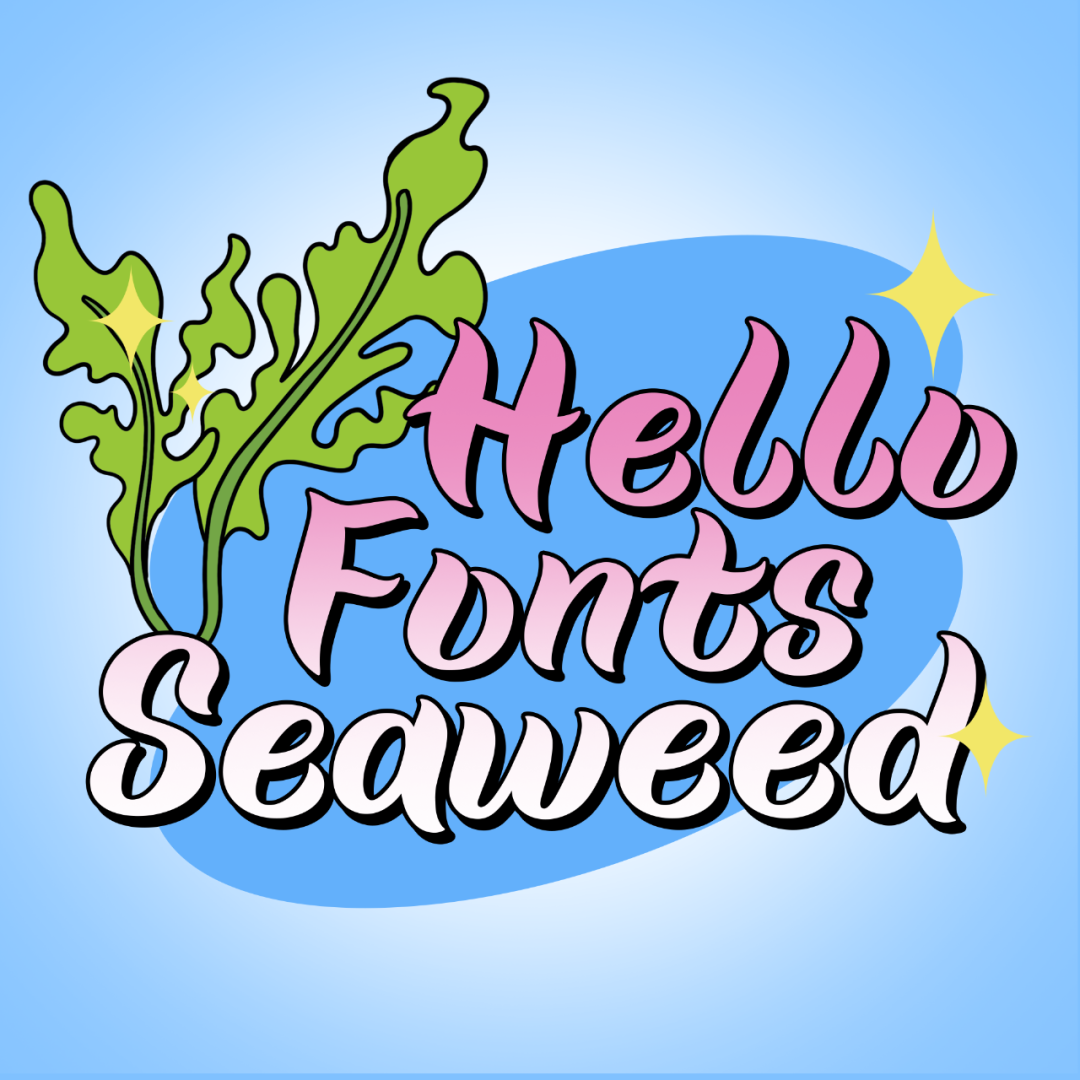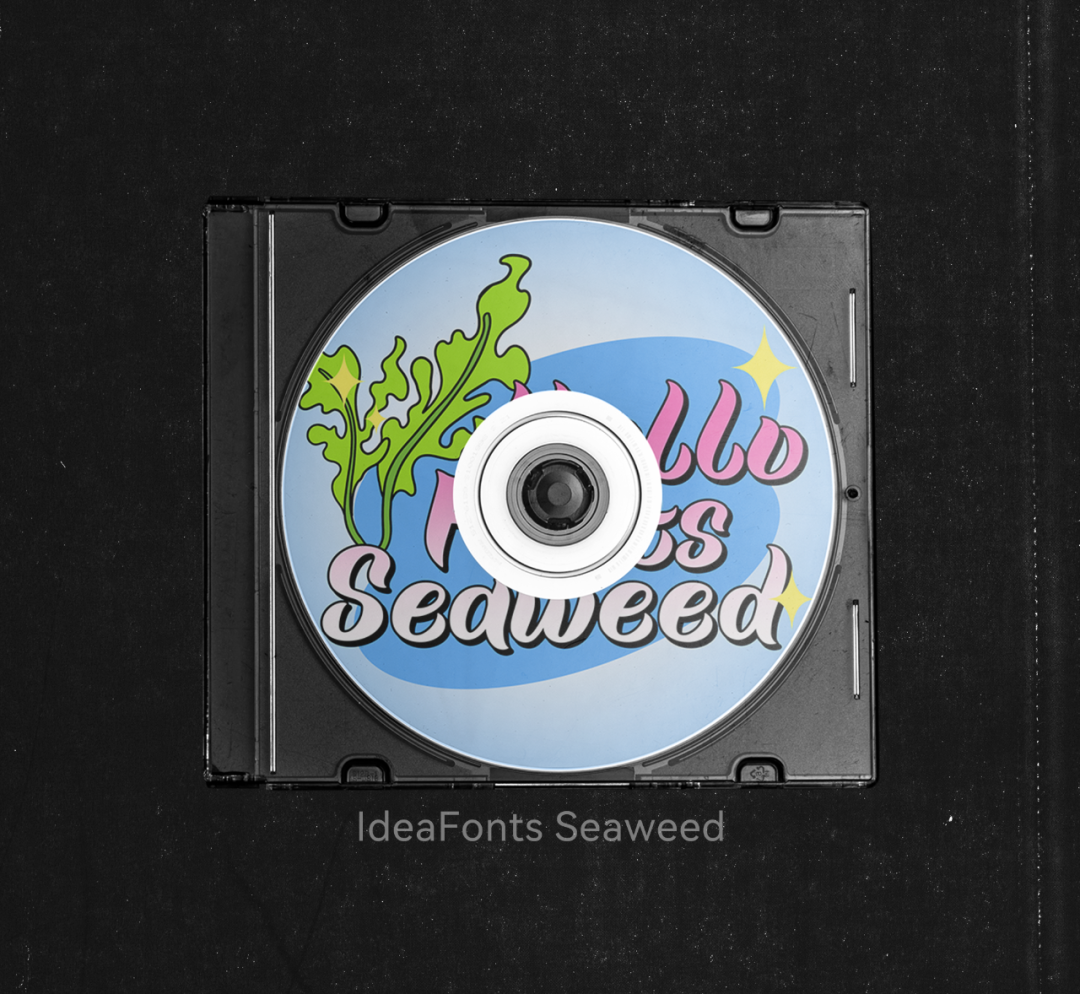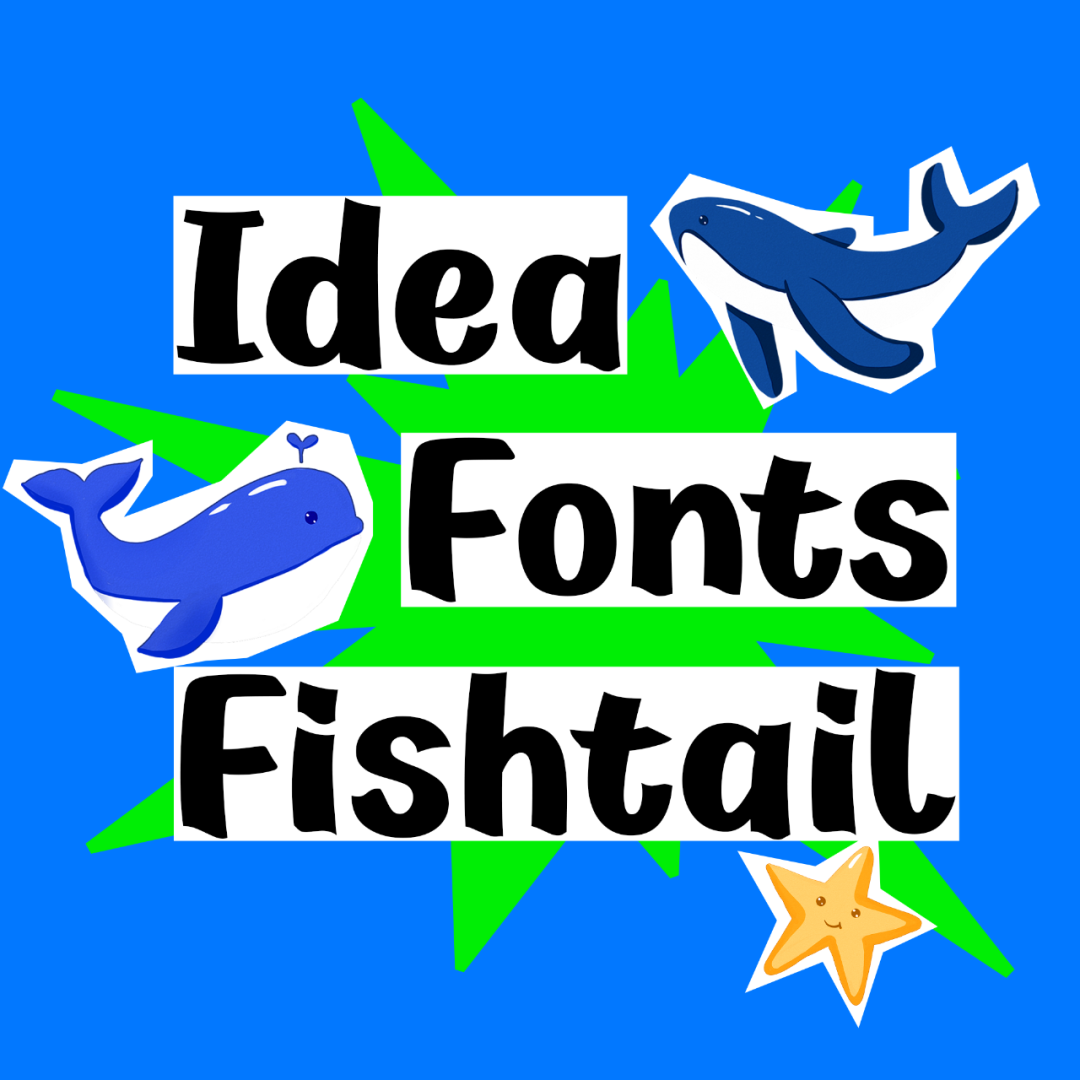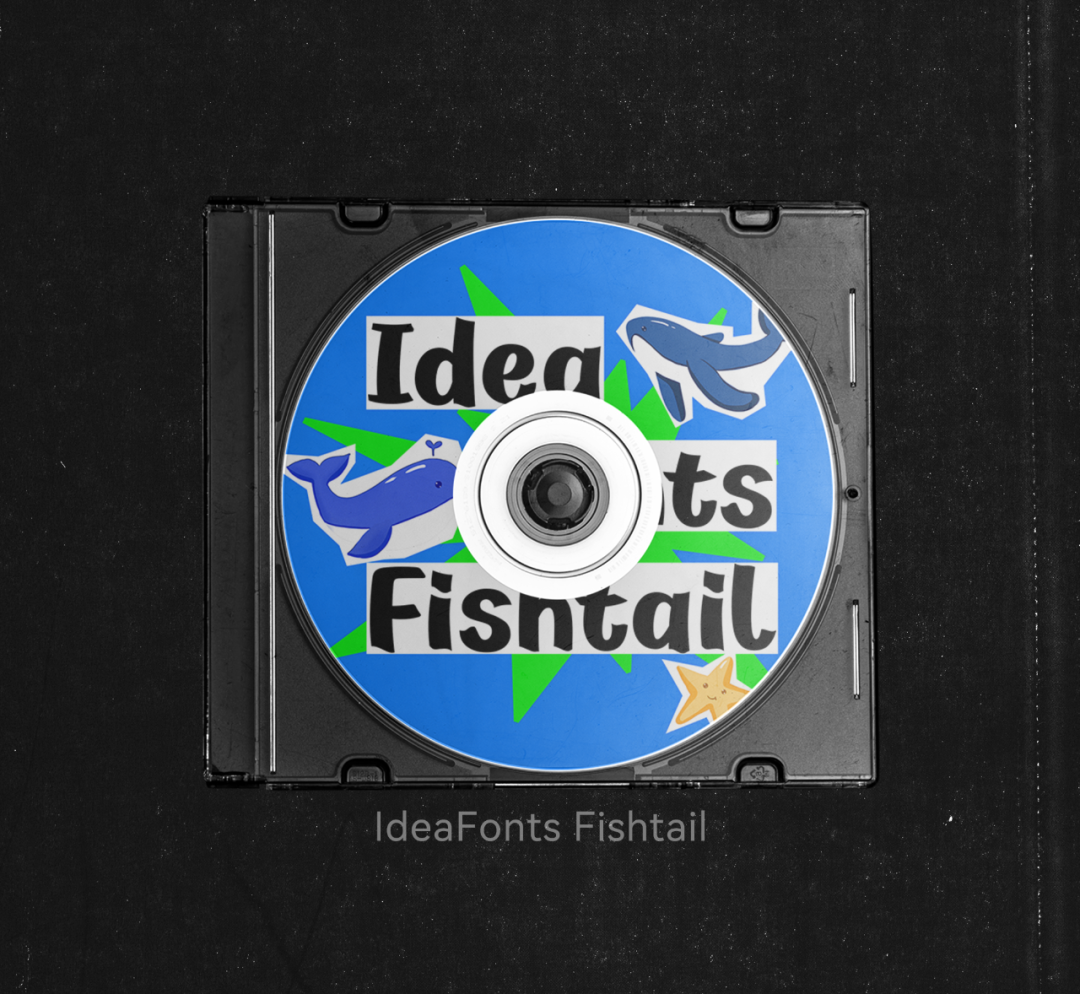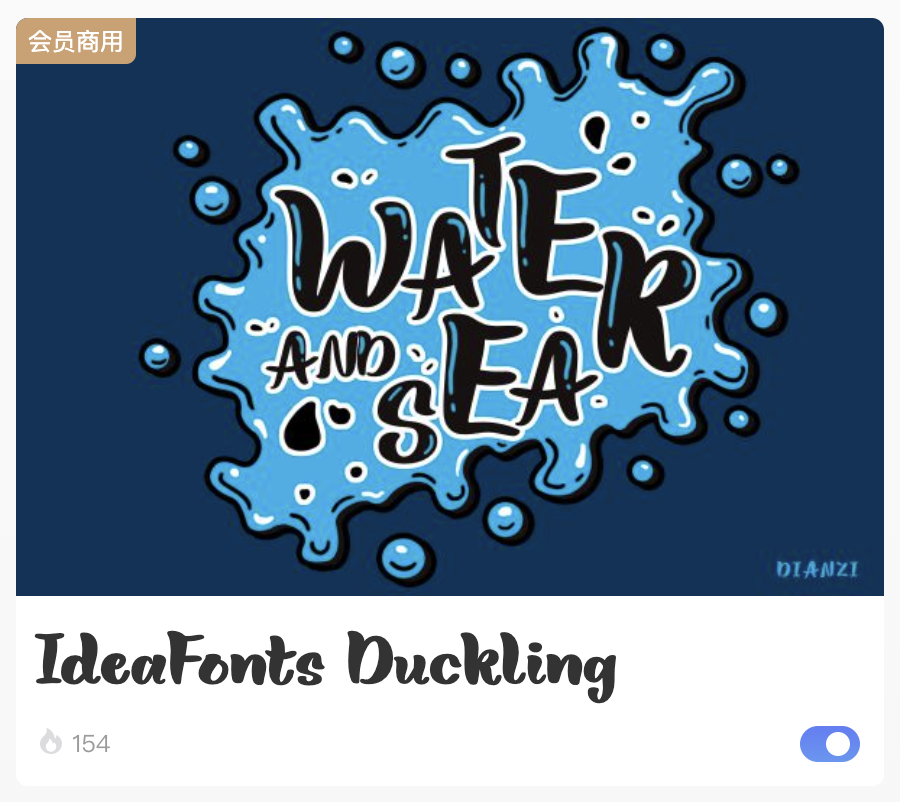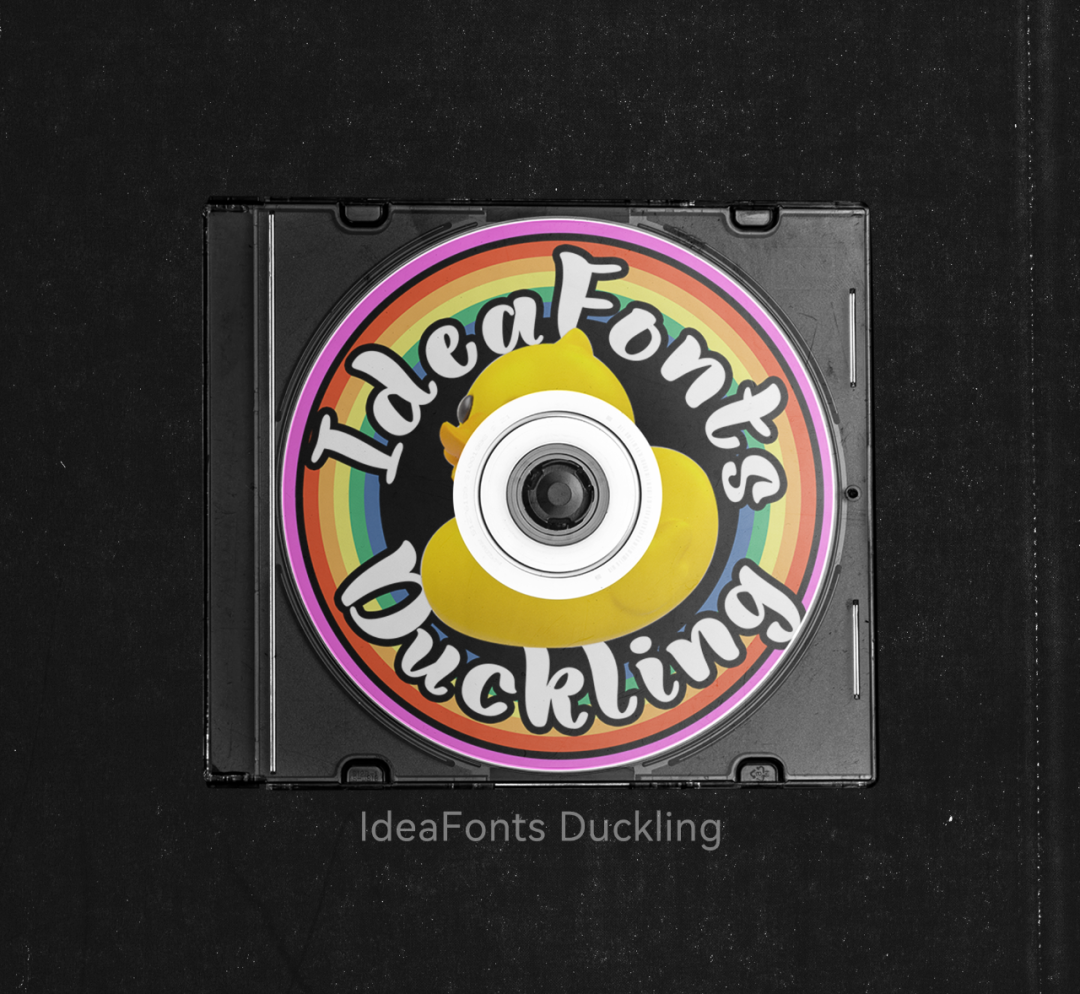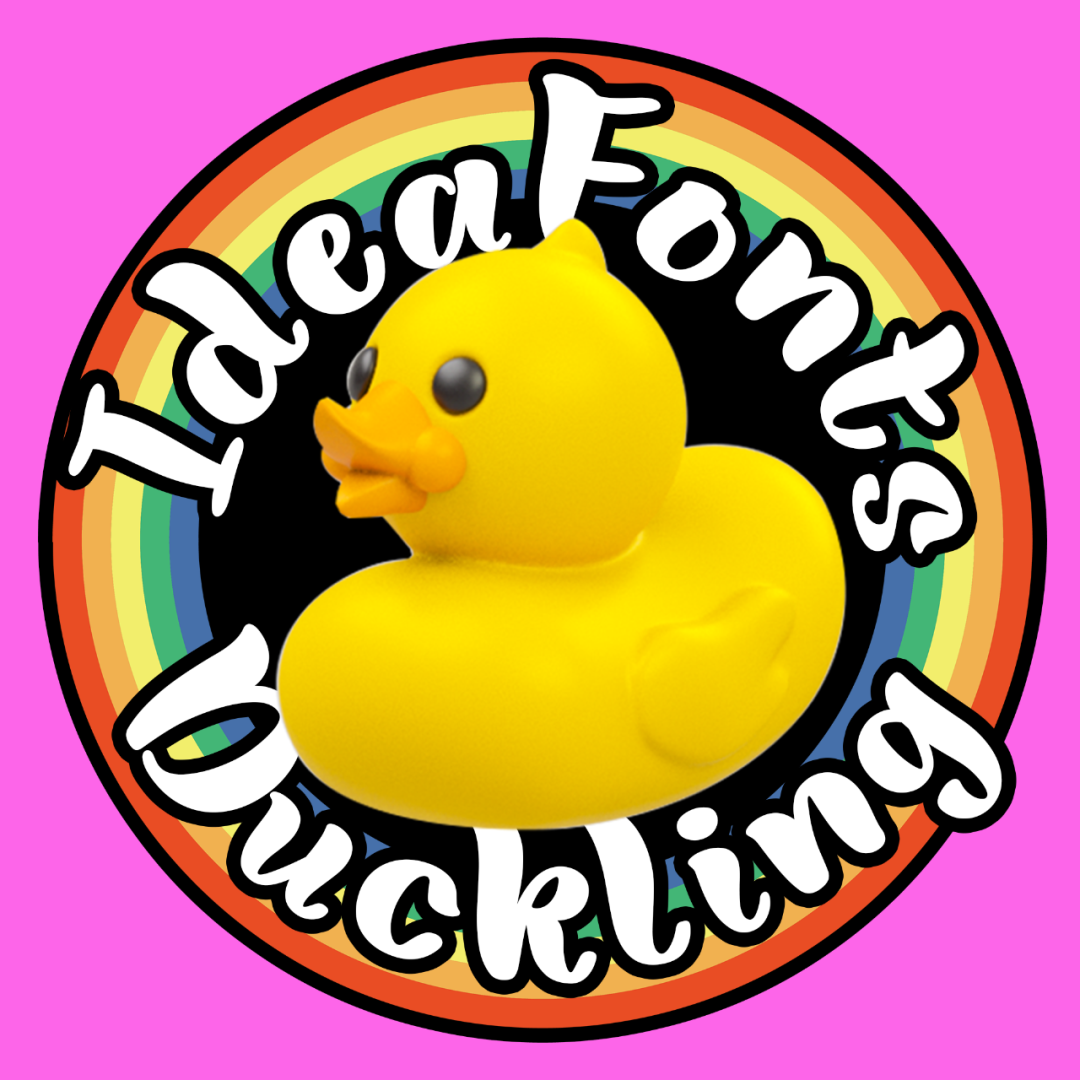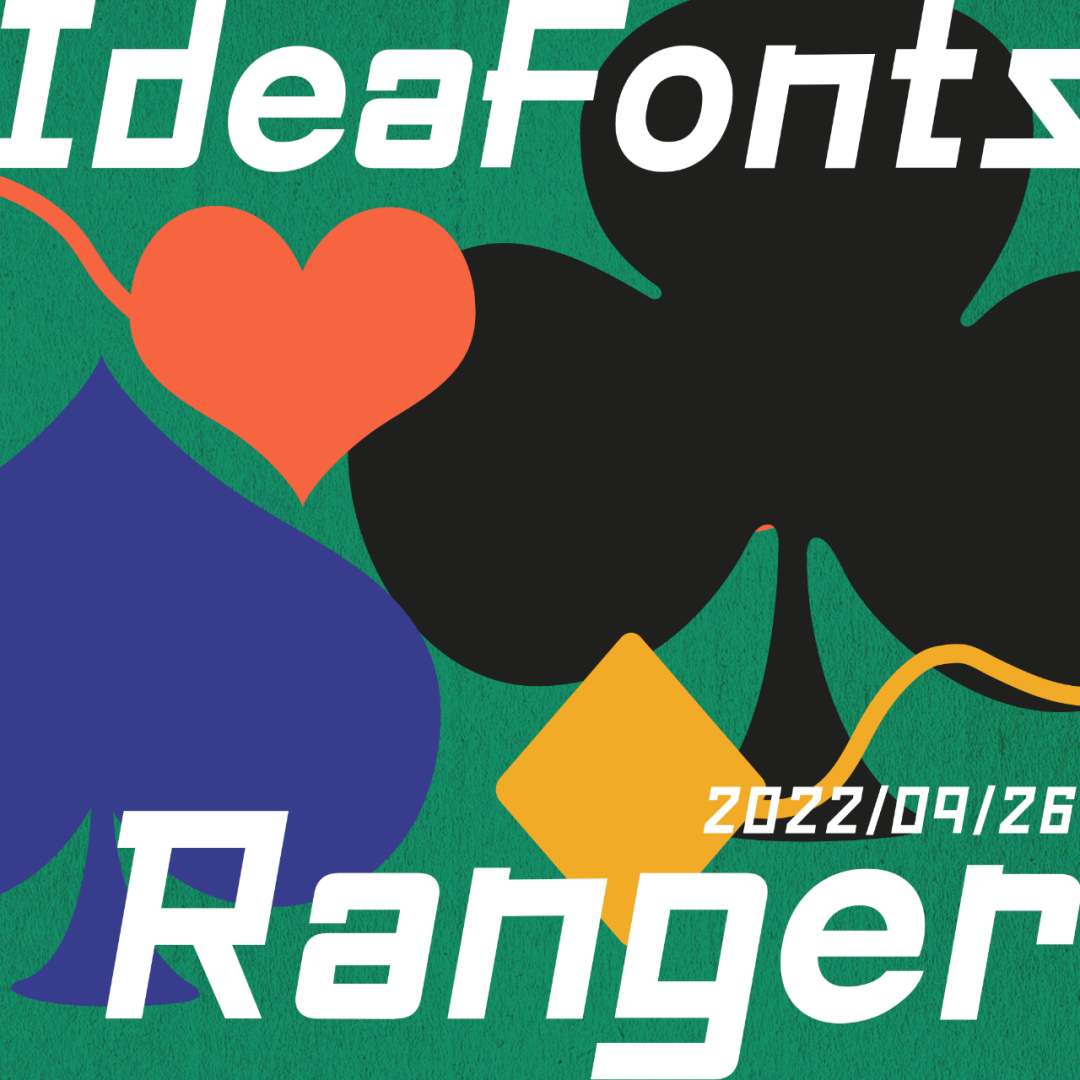
免费的英文字体这么多,为什么会员还要有?
是的,我摊牌了,别看字由上有889款免费字,但英文就占据了一大半,且各种风格应有尽有。这么多好看的字体,按理来说会员字体是完全没必要卷进这个赛道的。
所以基于此,字由准备在现有英文字体的基础上,继续推出一批好看、好用的字体。
首打的就是点字库出品的四款:
IdeaFonts Seaweed
第一款丝滑流畅,自带bgm,一看到它,脑海里就开始循环“像一颗海草海草海草海草,随波飘摇……”
IdeaFonts Fishtail
第二款像胖乎乎的小鱼,虽然只是黑白的字体,但仿佛能通过它看到五彩斑斓的海洋世界。
IdeaFonts Duckling
第三款字体完全是走可爱风格的~但是只要你用它,会发现意外地适合涂鸦风格呢。
IdeaFonts Ranger
最后一款不是手写字,但相信我,它很经典,既有横平竖直,又加了一点弧度,给人温暖可靠的感觉。